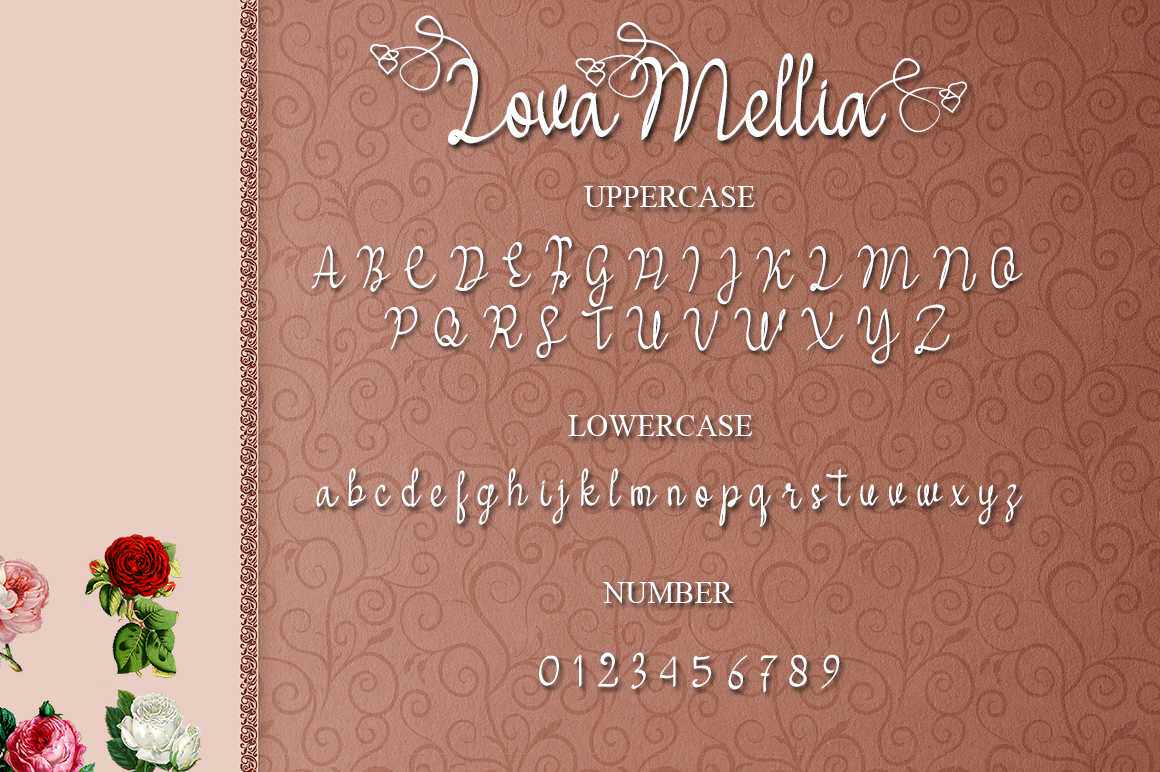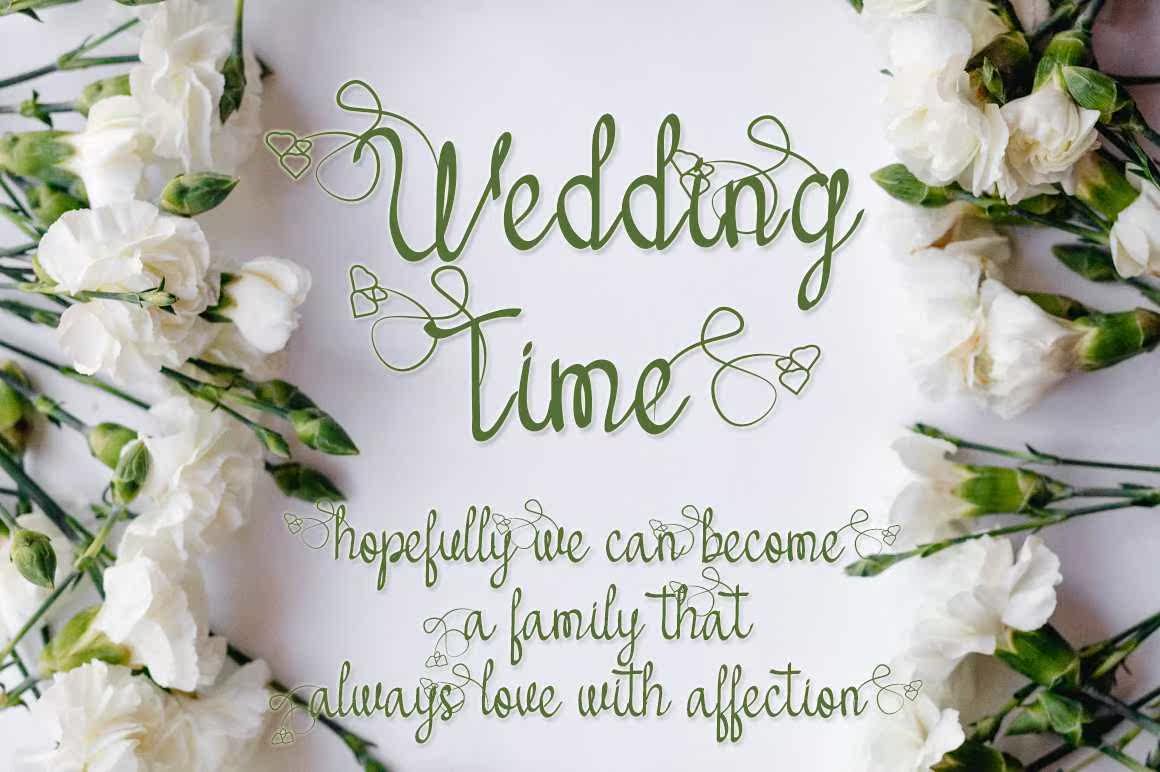
Lovamellia拥有完美的平衡和精致的手写字体。它是一款经典、优雅、现代的字体,可用于博客、品牌、邀请函、文具、婚礼设计、社交媒体等等!这个字体是经过编码的,意味着你可以访问所有的符号和SWASHEASE!Lovamellia拥有完美的平衡和精致的手写字体。它是一款经典、优雅、现代的字体,可用于博客、品牌、邀请函、文具、婚礼设计、社交媒体等等!这个字体是经过编码的,意味着你可以访问所有的符号和SWASHEASE!